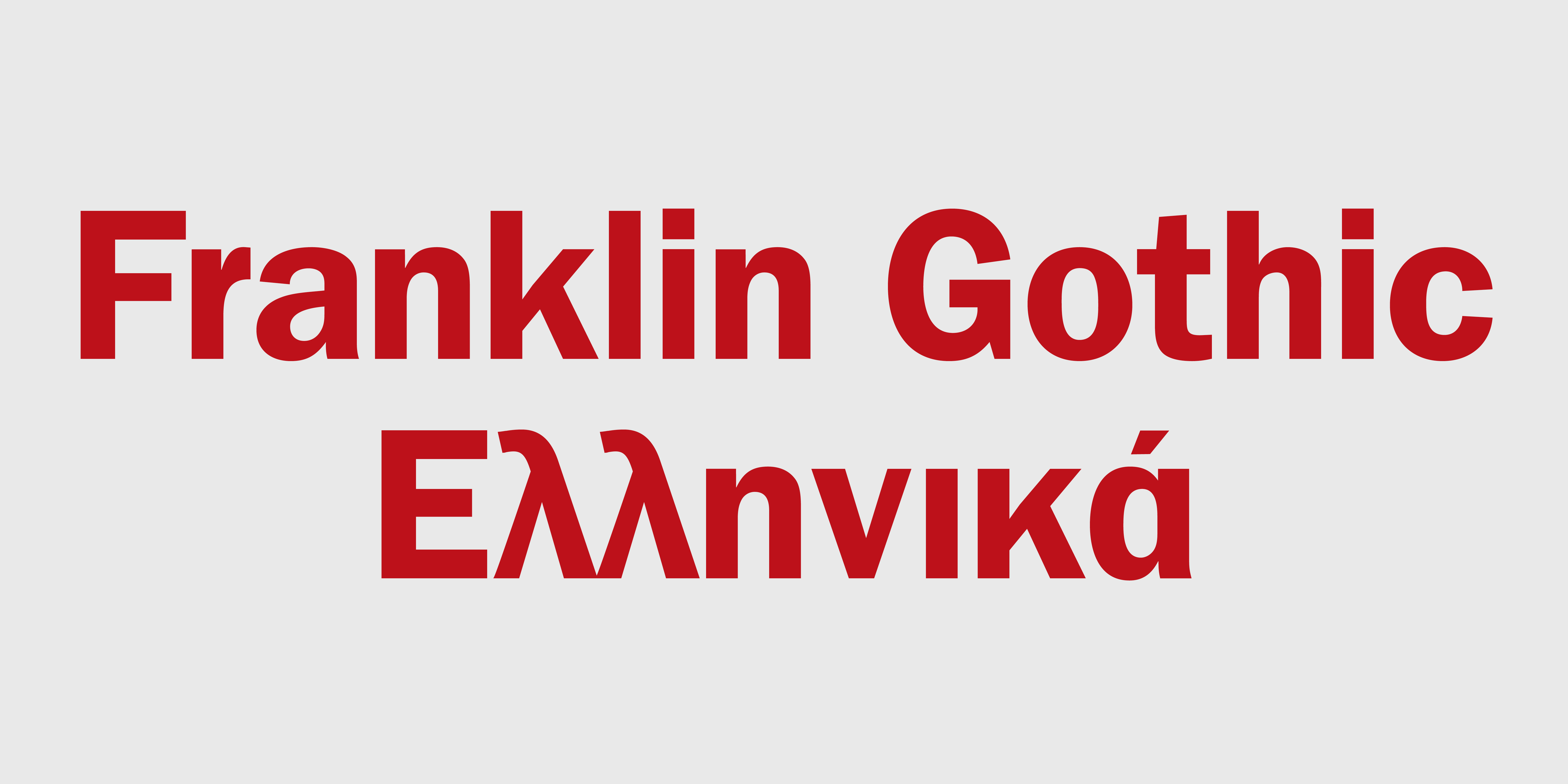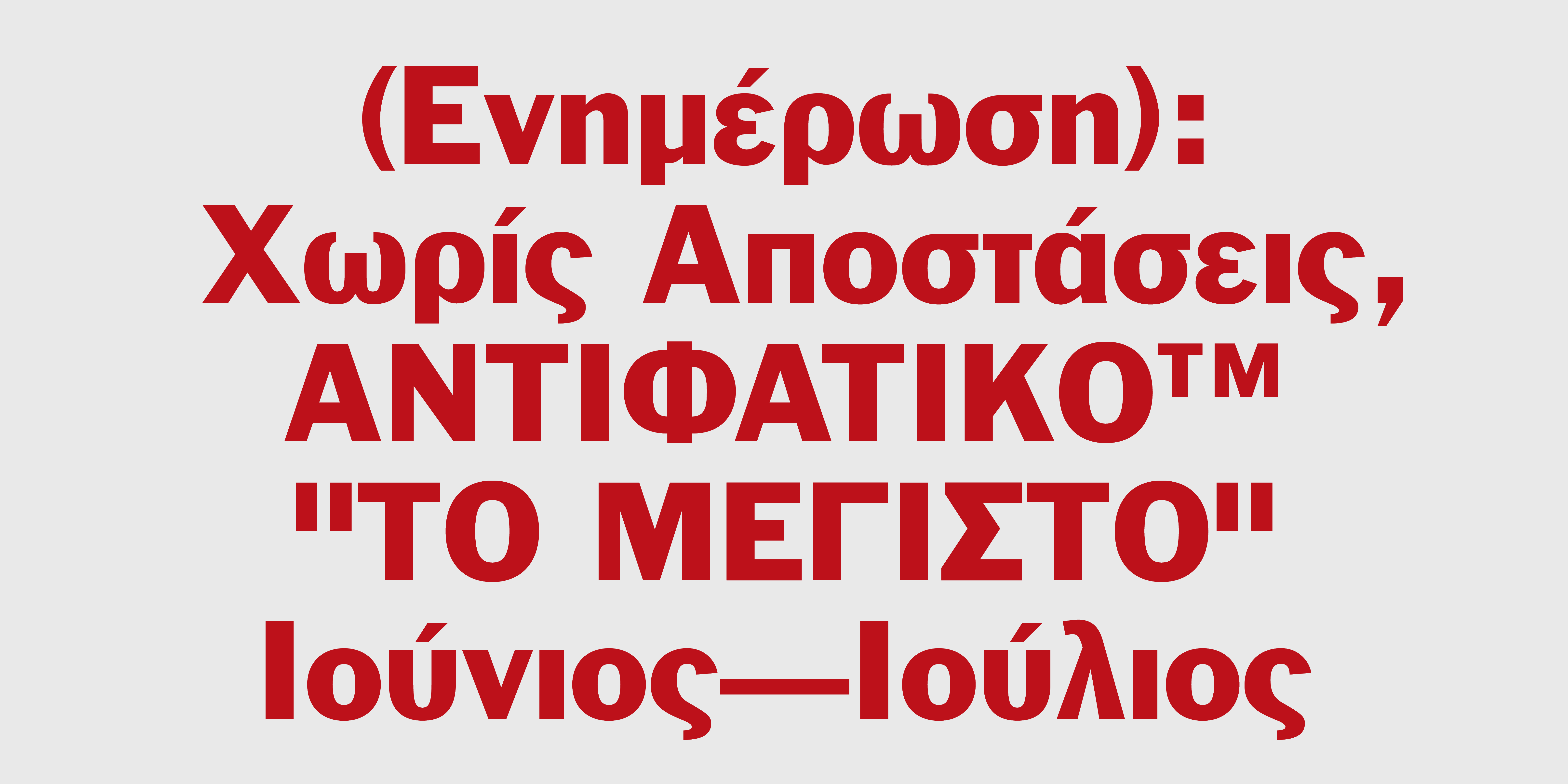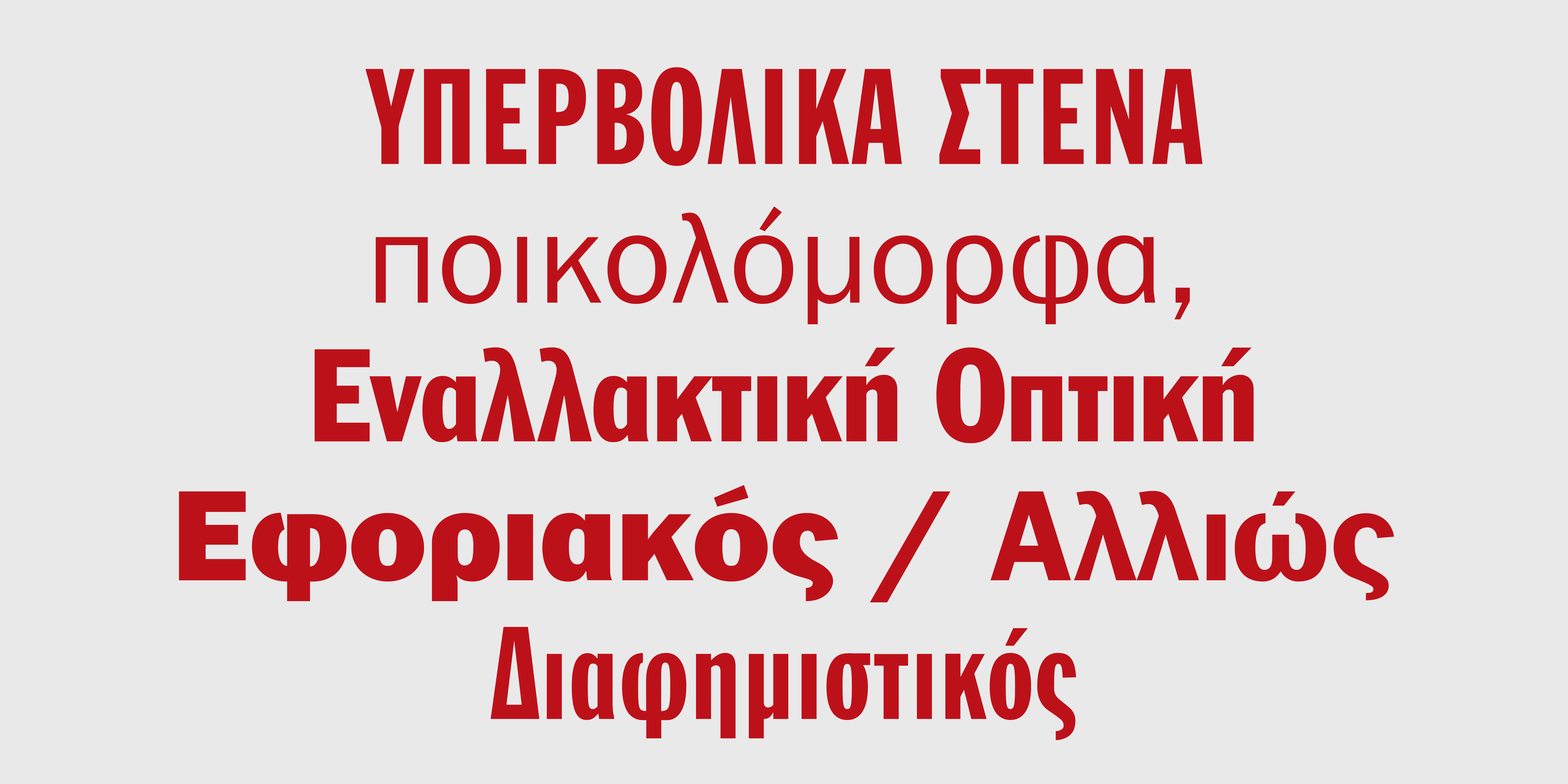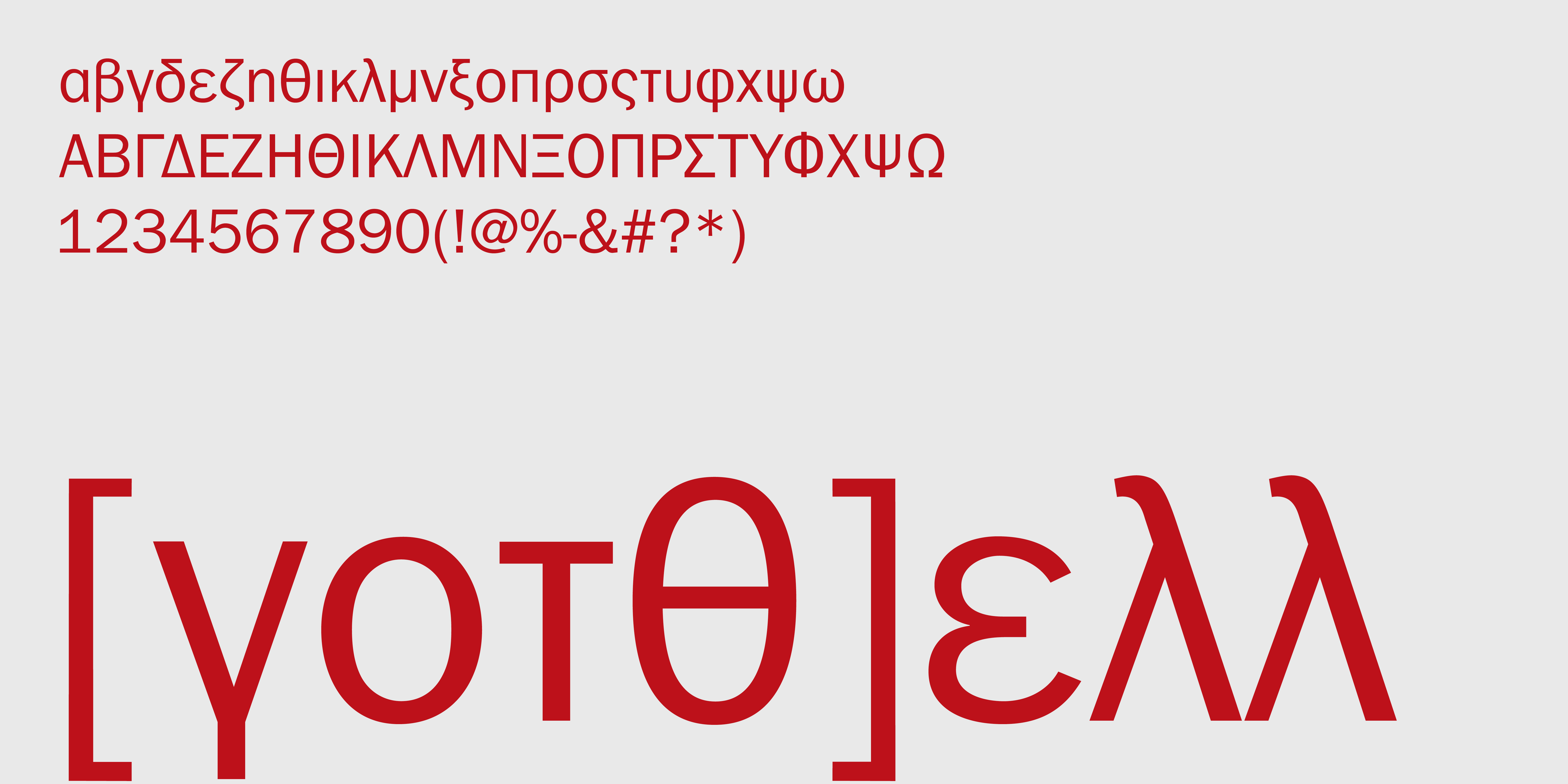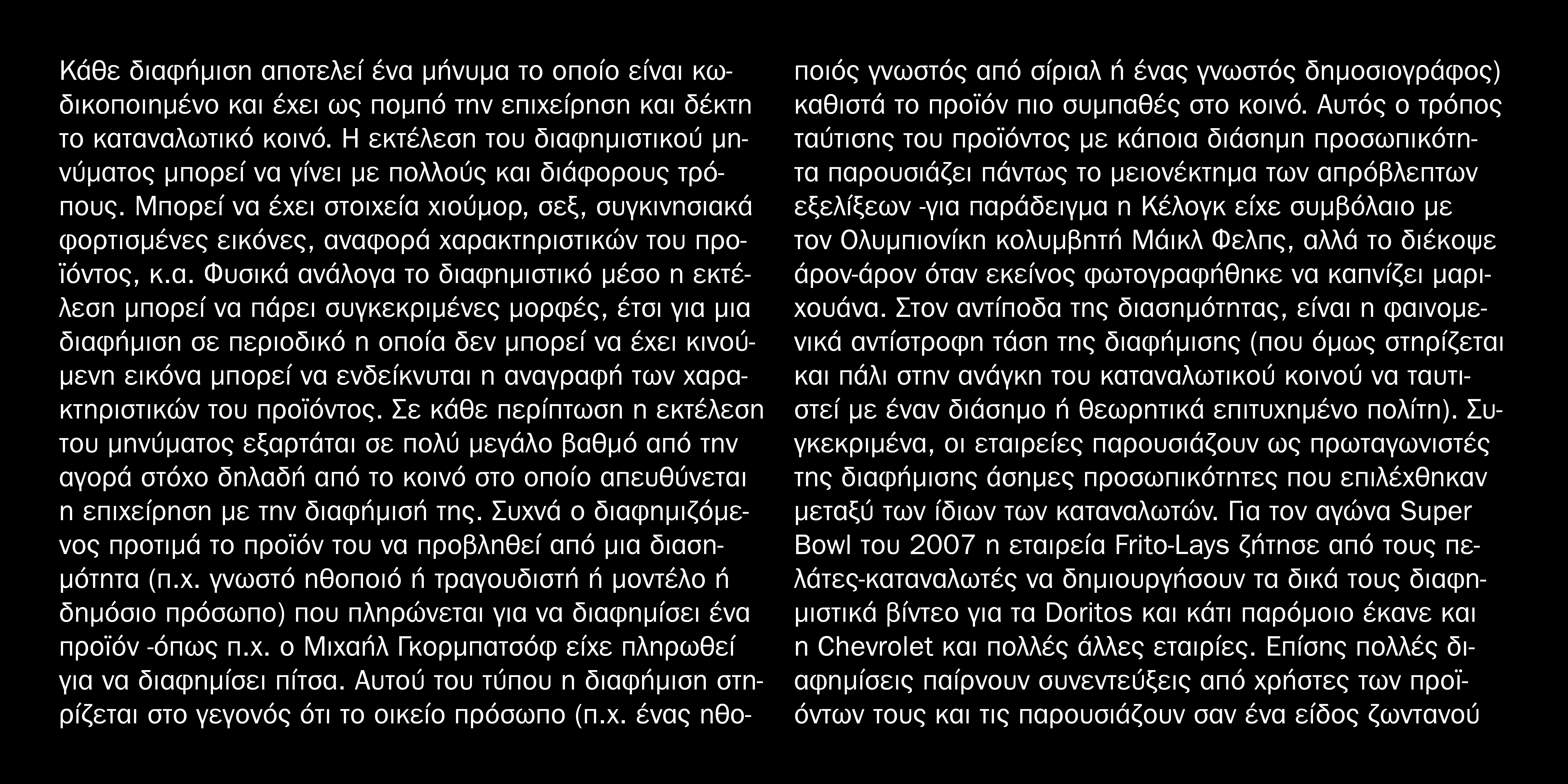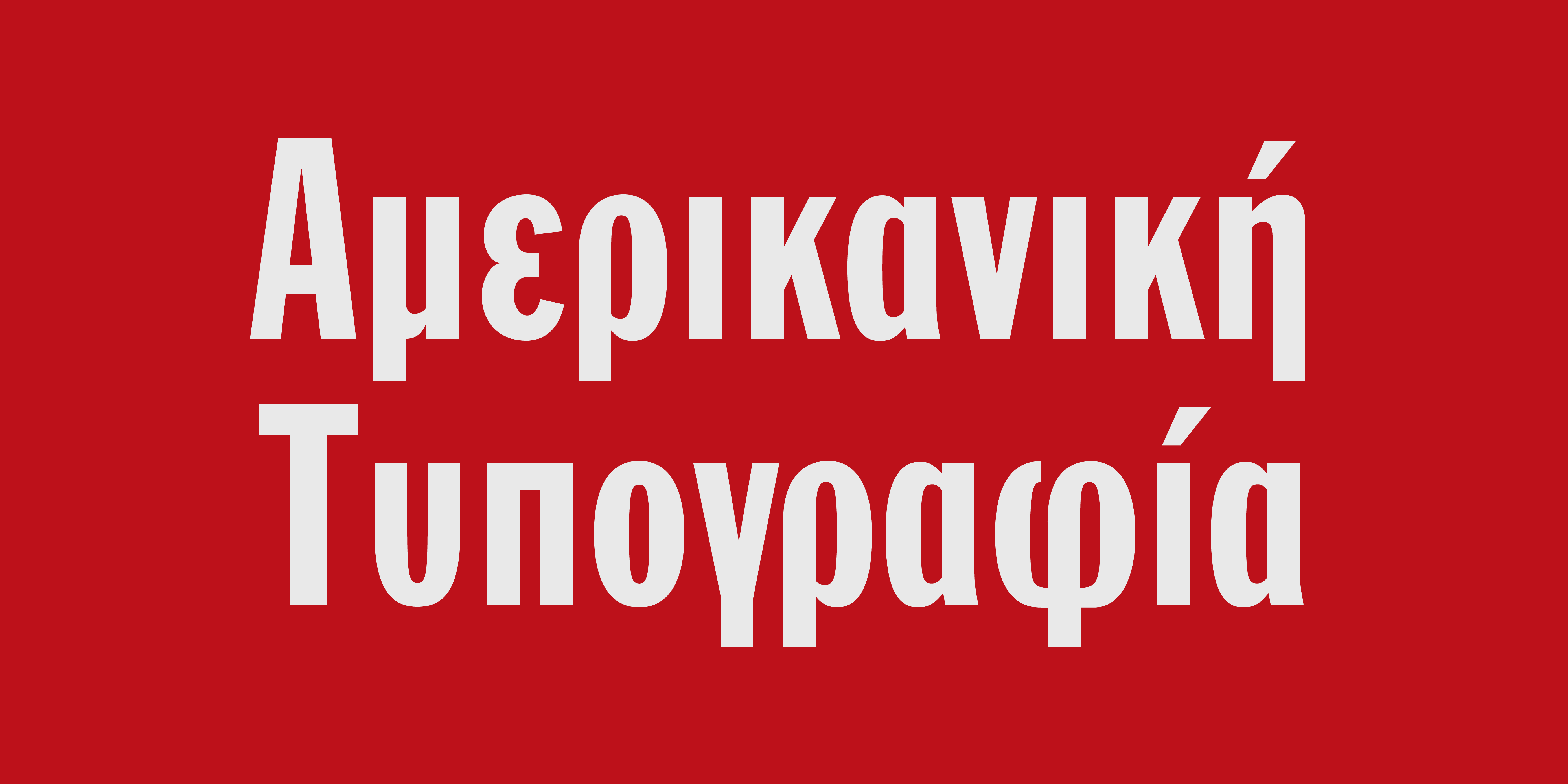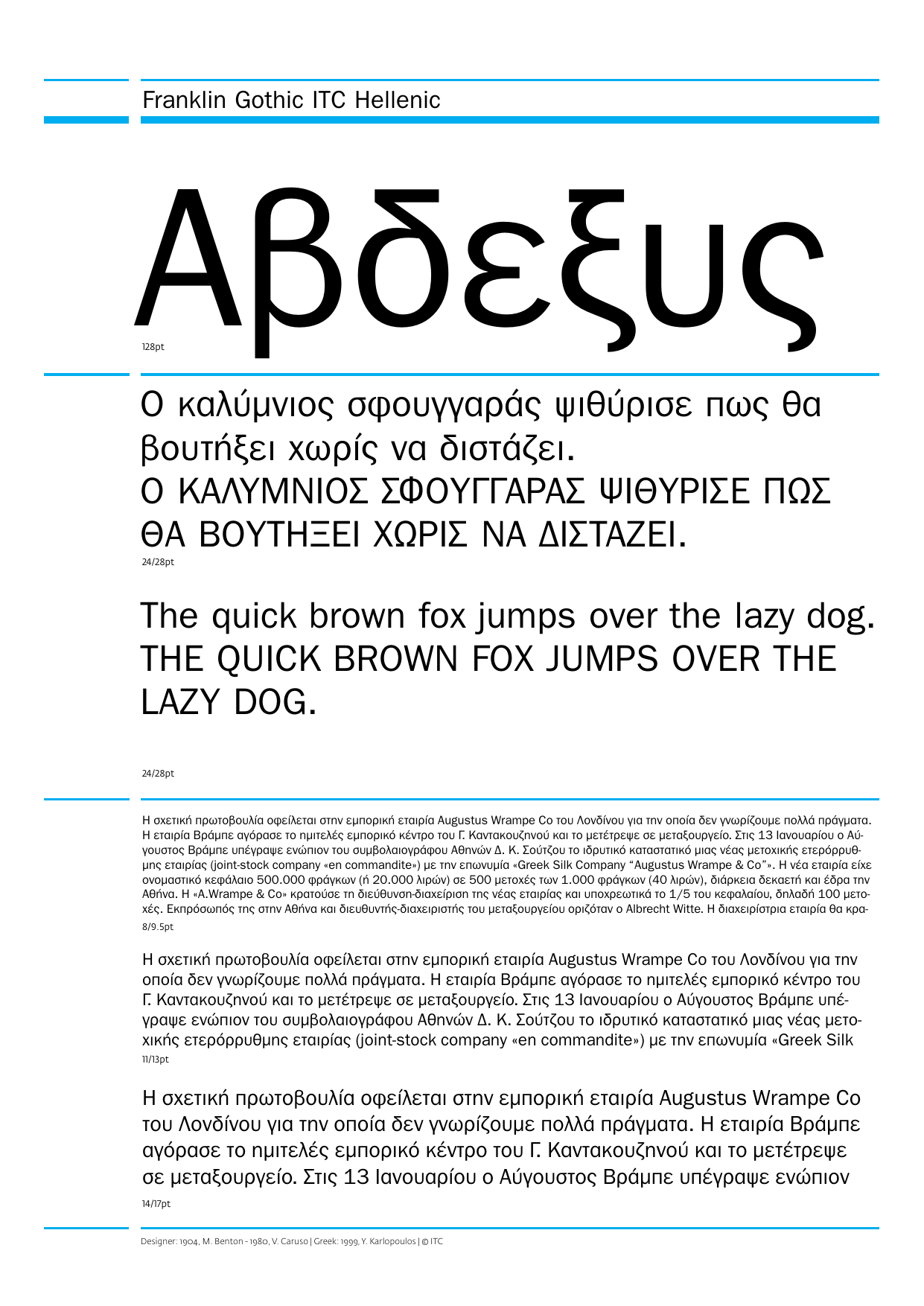
Franklin Gothic Ελληνικά
Δημιουργήθηκαν από την ΑTF το 1904 και είναι η προσωπική εκδοχή του Morris Fuller Benton πάνω στα βαριά ισόπαχα γράμματα που έγιναν αρχικά γνωστά το 1830 από τον Vincent Figgins. Η Franklin Gothic παραμένει ιδιαίτερα δημοφιλής ακόμα και μετά από τόσα χρόνια χρήσης.